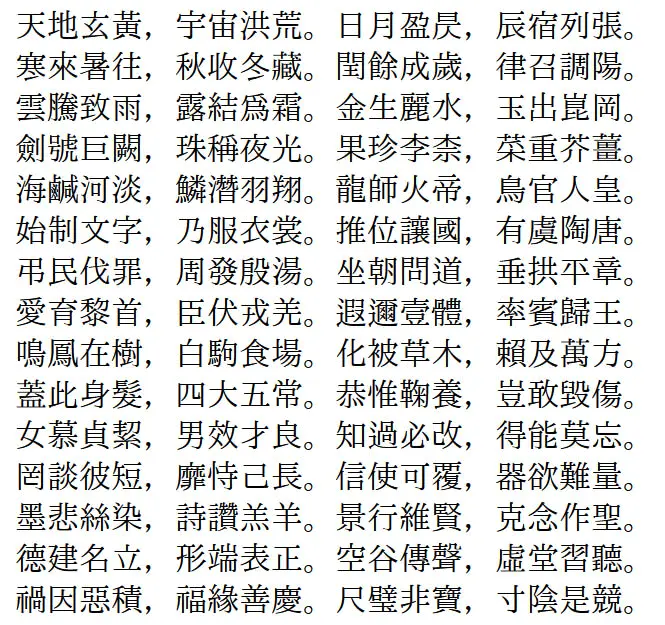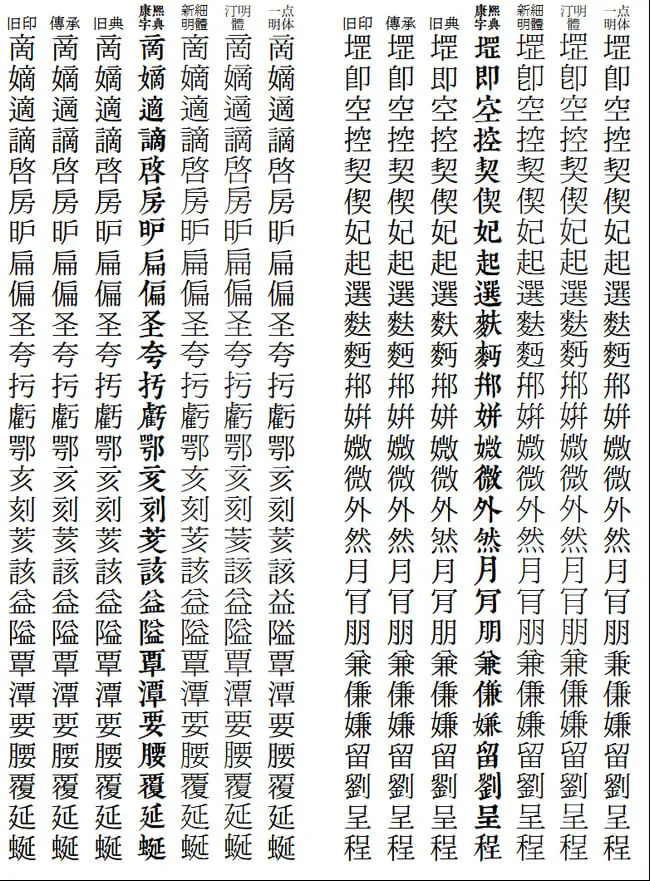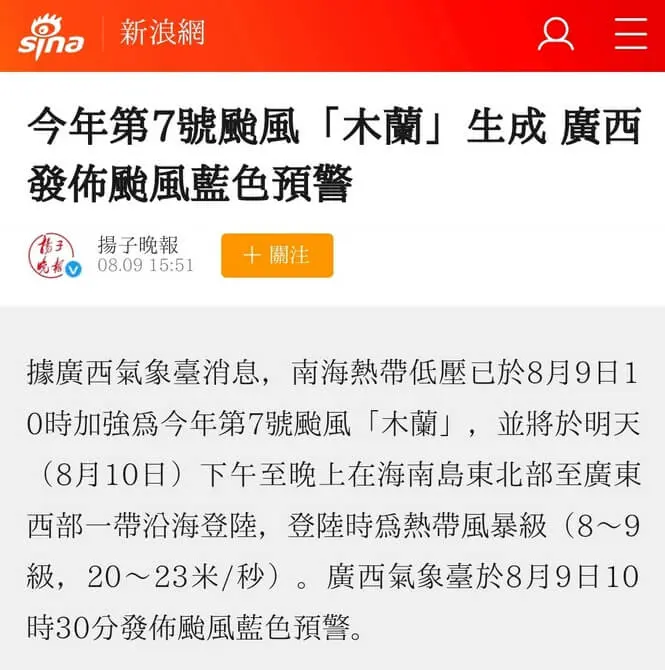
華英明朝(Huaying Mincho)是一套擁有傳承字形、舊字形風格的中文字體。華英明朝共提供 3 種字形風格,並帶有符合 IVD_Charts_Moji_Joho 標準的異體選擇器。
1.華英明朝舊印體
舊印刷體,字形接近舊版Windows新細明體。
2.華英明朝傳承體
傳承字形,字形部件較為統一。
3.華英明朝舊典體
接近《康熙字典》中的字形,字形部件不統一。
4.華英明朝繁體
由傳承體修改,簡入繁出的字體,可根據文字內容動態匹配一簡多繁的情況。
傳承體預覽
版本對比
繁體版預覽(文字為簡體)